أفضل خطوط الويب المجانية لعام 2018
نشرت: 2018-10-26تلعب الخطوط التي تختارها لموقع WordPress الخاص بك دورًا كبيرًا في التصميم العام. إنها ليست فكرة متأخرة بأي حال من الأحوال. ما عليك سوى تغيير جميع عناوينك إلى Comic Sans إذا كنت بحاجة إلى رؤية دليل! حسنًا ، هذا متطرف بعض الشيء. ولكن مع الطباعة ، حتى أصغر تغيير يمكن أن يحدث فرقًا كبيرًا. بفضل الويب (وخاصة Google) ، هناك الكثير من خطوط الويب المجانية المتاحة لمساعدتك في اختيار أفضلها. لذلك ، إذا كنت تبحث عن القليل من الإلهام أو عن ترقية خط لموقعك الحالي ، فإنني أوصيك بشدة بتصفح القائمة أدناه لاستكشاف بعض أفضل خطوط الويب التي يقدمها عالم التصميم.
أفضل خطوط الويب المجانية لعام 2018
فيما يلي 40 من أفضل خطوط الويب المتوفرة في 2018 (وهي مجانية!)
1. روبوتو
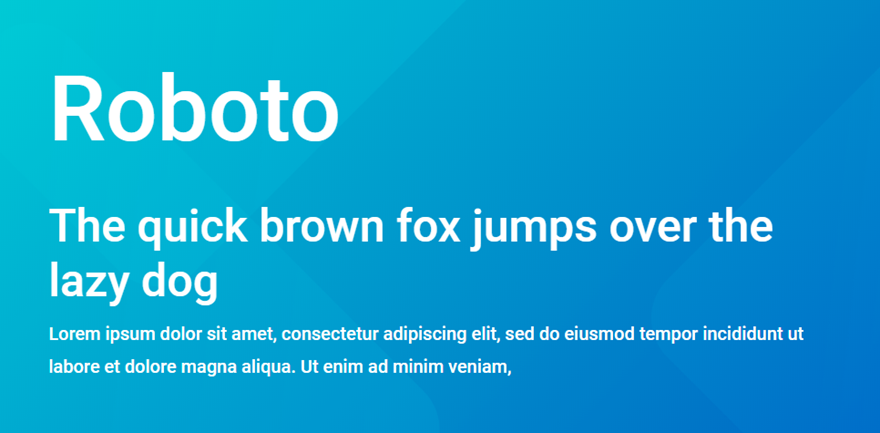
من المفترض أن يكون Roboto عبارة عن زواج بين الأشكال الهندسية والمنحنيات الودية. ينشئ إيقاعًا طبيعيًا للقراءة ويعمل بشكل جيد مثل العنوان أو نوع الجسم. النسخة المكثفة ، Roboto Condensed ، تحظى بشعبية كبيرة أيضًا.
2. عرض Playfair
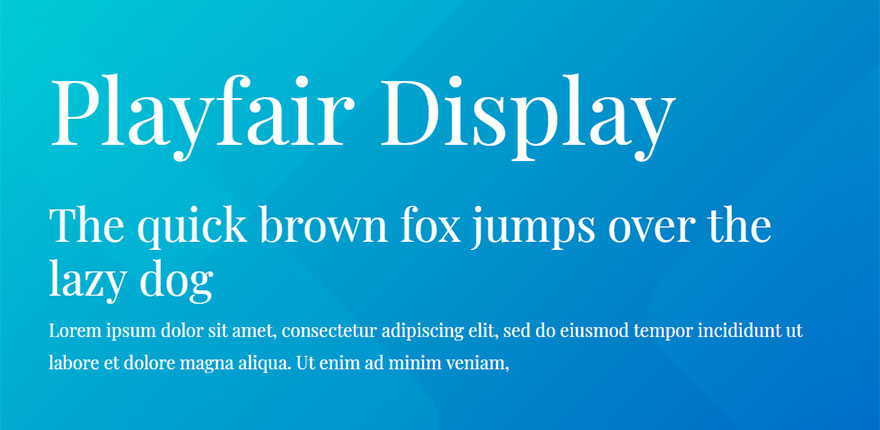
تأثر Playfair بانتقال تكنولوجيا الكتابة / الطباعة في أواخر القرن الثامن عشر ؛ عندما تم استبدال الريش بأقلام فولاذية مدببة. كما أنها متأثرة بمحرف جون باسكرفيل ومحرف ويليام مارتن لـ "Boydell Shakspeare". إنه رائع للعناوين والعناوين.
3. افتح Sans
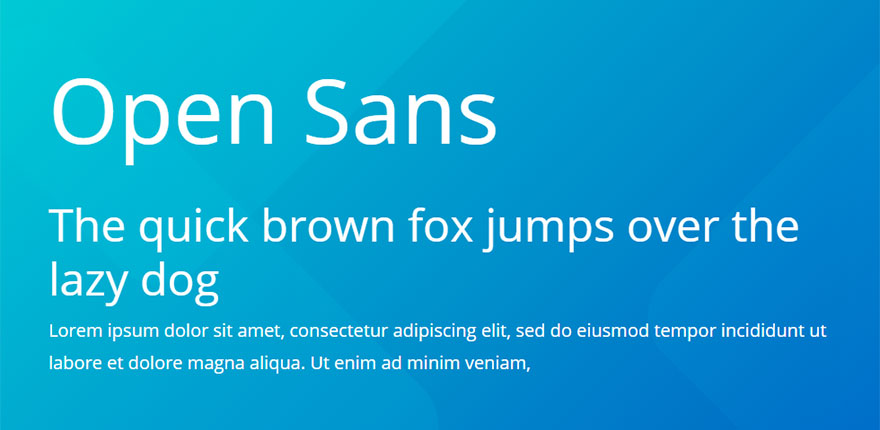
تم تصميمه كوجه محايد جيد Open Sans ودود للغاية ويمكن قراءته. جيد للعناوين أو النص الأساسي.
4. مونتسيرات
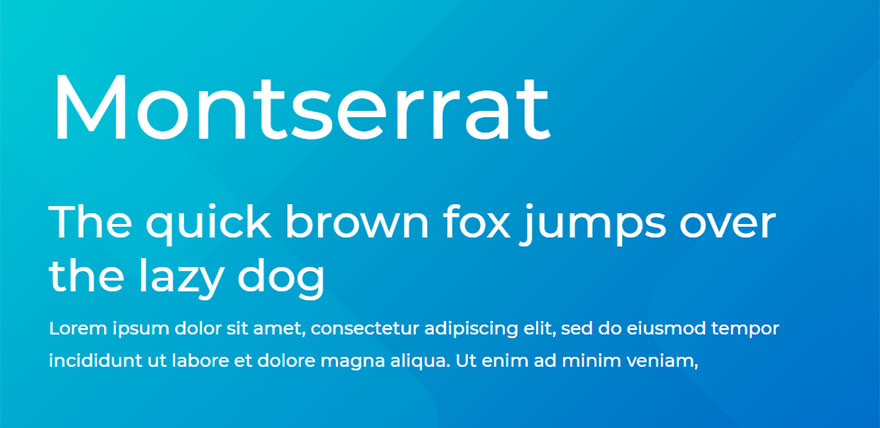
تم إنشاء هذا الخط في الأصل بواسطة Julieta Ulanovsky. جاء إلهامها لتصميم الخط من كل اللافتات والملصقات الجميلة التي شاهدتها في مونتسيرات ، أحد أحياء بوينس آيرس. يبدو رائعًا في العناوين القصيرة ذات الأحرف الكبيرة في جميع الأحرف الكبيرة.
5. ميريويذر
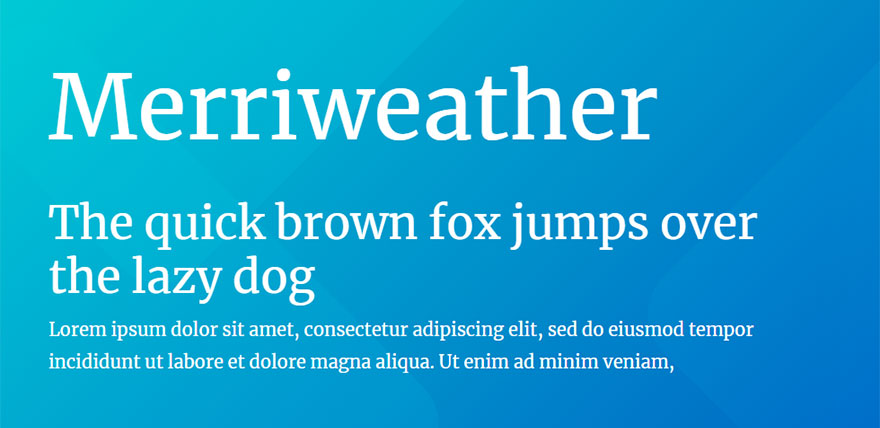
يعد محرف serif هذا ممتعًا للغاية للقراءة في النص الأساسي على جميع أنواع الشاشات لأنه تم تصميمه للويب. كما أنه يعمل بشكل رائع مع العناوين أيضًا.
6. لاتو
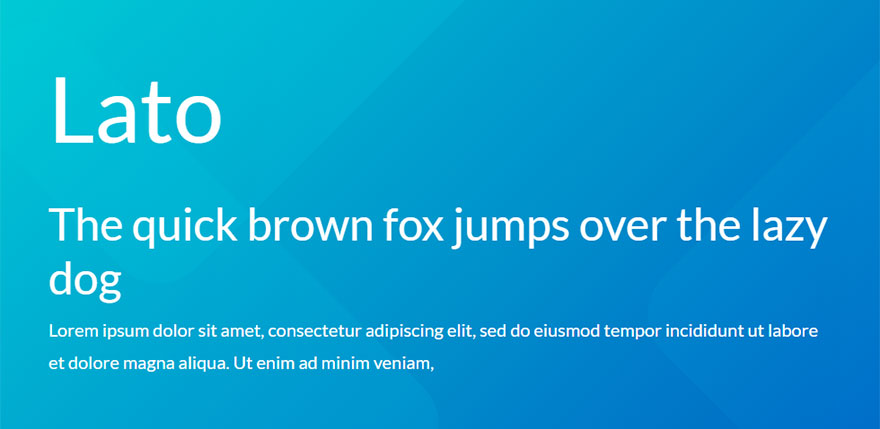
تم تصميم Lato خصيصًا لاستخدام الشركات. تتمتع بمظهر احترافي يناسب الاستخدام بأحجام مختلفة. كما أن تفاصيله شبه الدائرية تضفي عليه الدفء الذي يروق للجماهير.
7. بيباس نيو
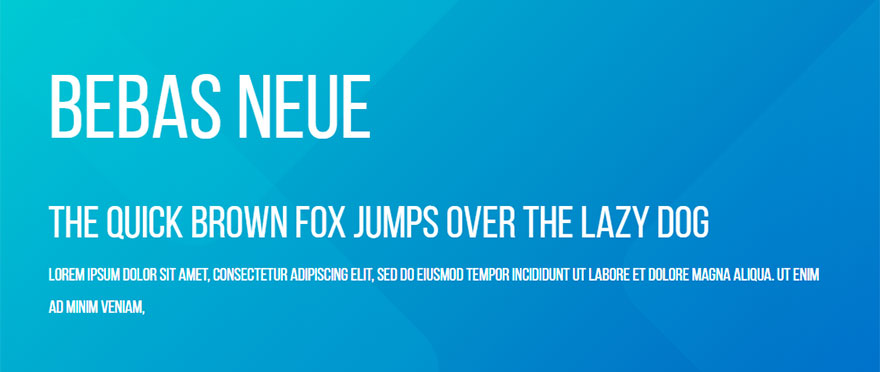
هذا الخط sans serif “all Caps” شائع للغاية ويعتبر أحد أفضل خطوط الويب المجانية لسبب وجيه. يقوم بإنشاء عروض رائعة المظهر لرؤوس موقع الويب الخاص بك!
8. نوتو بلا
يعد Noto Sans فريدًا من حيث أنه تم إنشاؤه ليبدو رائعًا عبر لغات متعددة. نظرًا للتباعد الأفقي بين الأحرف ، فإنها تبدو رائعة على النص الأساسي وعلى الصفحات التي تحتوي على الكثير من المحتوى.
9. المصدر بلا برو
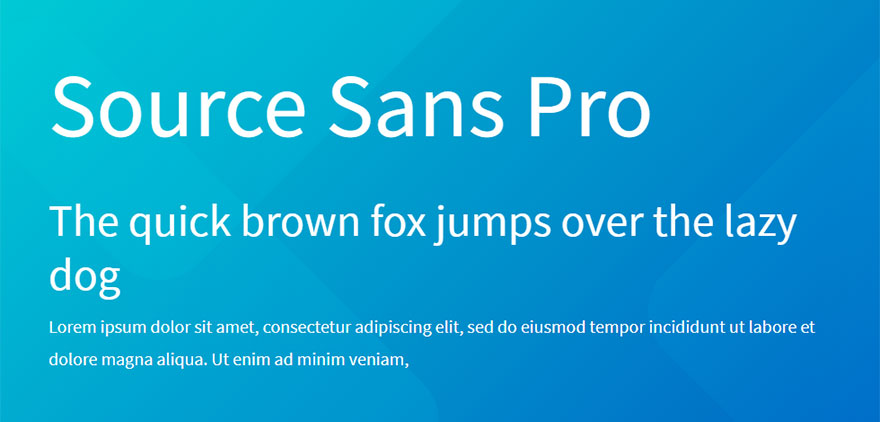
تم تصميم Source Sans Pro بشكل أساسي مع وضع واجهات المستخدم في الاعتبار. سيؤدي هذا إلى إنشاء خط قائمة رائع ولكن يمكن استخدامه أيضًا لأشياء أخرى مثل النص الأساسي.
10. أوزوالد
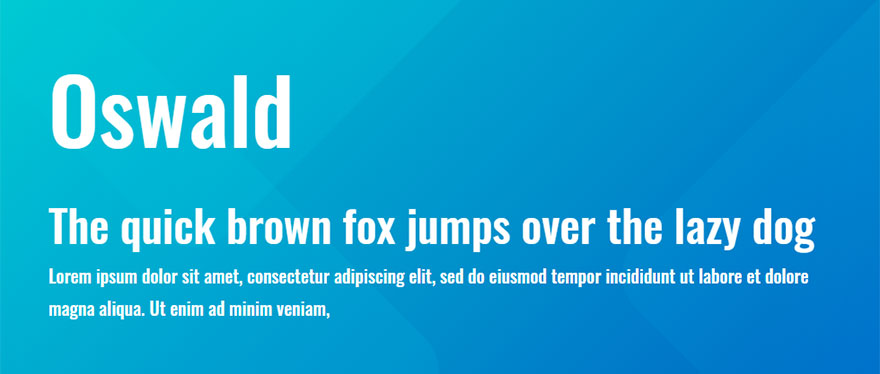
يعد محرف sans serif هذا خطًا رائعًا للويب لأنه تم تشكيله ليلائم شبكة البكسل للشاشات الرقمية. إنه خط ضيق لا يشغل مساحة كبيرة لذا فهو يعمل بشكل رائع مع العناوين الكبيرة التي تحتوي على الكثير من النصوص.
11. PT بلا
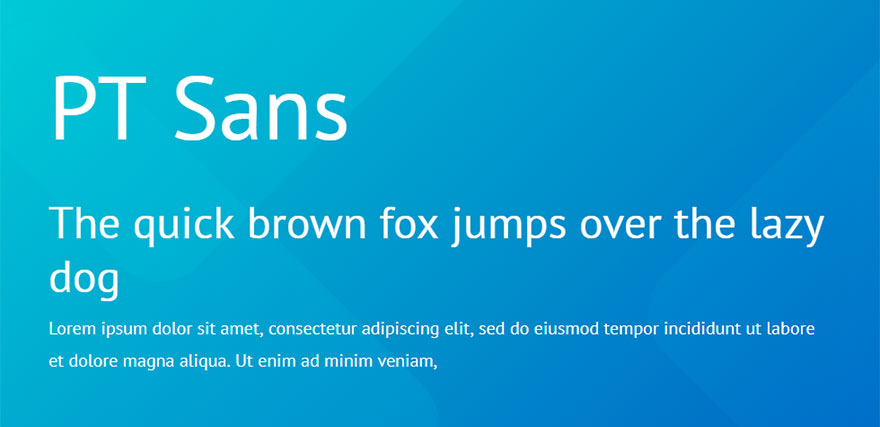
يعد PT Sans جزءًا من مشروع يسمى "الأنواع العامة للاتحاد الروسي" الذي يهدف إلى جعل عرض النص بلغات متعددة موحدًا (على غرار Noto Sans). هذا الخط جيد لأغراض متعددة.
12. روبيك
تم تصميم خط rubik بواسطة Philipp Hubert و Sebastian Fischer لإنشاء خط sans serif بزوايا دائرية قليلاً تتناسب فيها الحروف تمامًا داخل مربعات مكعب روبيك. يعمل الخط بشكل رائع مع كل من العناوين والنص الأساسي.
13. نونيتو سانس
هذا الخط sans-serif هو نسخة غير دائرية من Nunito. إنه خط شائع لواجهات المستخدم ويبدو رائعًا لأشياء مثل لوحات المعلومات وقوائم المطاعم وقوائم الأسعار.
14. فيرا سانس
تم تصميم خط الويب الشهير هذا في الأصل لـ Mozilla FirefoxOS لوضوح واضح على جميع أحجام الشاشات. استخدمه كنوع حديث لأغراض متعددة.
15. عمل بلا
تم تصميم خط sans serif هذا كخط ويب مبسط يبدو رائعًا على جميع الشاشات. استخدم أوزانًا أثقل لشاشات العناوين الكبيرة الواسعة والوزن العادي للنص الأساسي الذي يسهل قراءته.
16. بوبينز
Poppins هو محرف هندسي حديث من sans serif يعتمد على تصميم Devanagari الذي يسلط الضوء على شكل الدائرة الهندسية لهذا الخط الجميل. لا تتردد في استخدام هذا الخط لكل من العناوين والنص الأساسي لتصميم يرضي العين للغاية.
في حالة عدم ملاحظتك ، فهو أيضًا الخط المستخدم في مدونتنا.
17. جوزفين سانس
هذا الخط هو أخت جوزفين سلاب (خط رائع أيضًا). تم تصميمه ليكون أنيقًا هندسيًا ولإضفاء طابع كلاسيكي. استخدم تباعد الأحرف السلبي للعناوين الأكبر ويمكنك الاحتفاظ بمسافة الأحرف الافتراضية الرائعة التي يوفرها لك النص الأساسي.
18. أوبونتو
Ubuntu هو خط sans-serif مصمم للويب ويقصد به أن يكون خطًا للأغراض العامة. مناسب للعناوين والأزرار والنص الأساسي على حدٍ سواء.
19. بي تي سيريف
PT Serif هي الإضافة الجديدة إلى عائلة PT Sans ، لذا يعمل الاثنان معًا بشكل جيد كإقران خط. إنه نوع متناغم يعمل جيدًا لأي شيء تقريبًا.